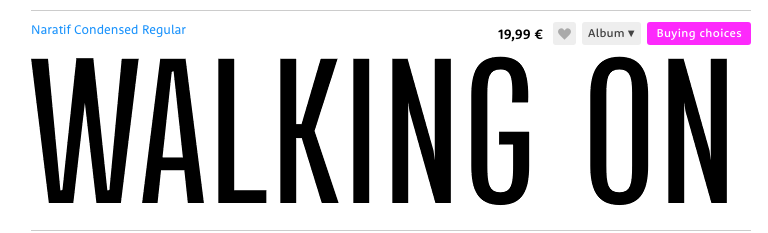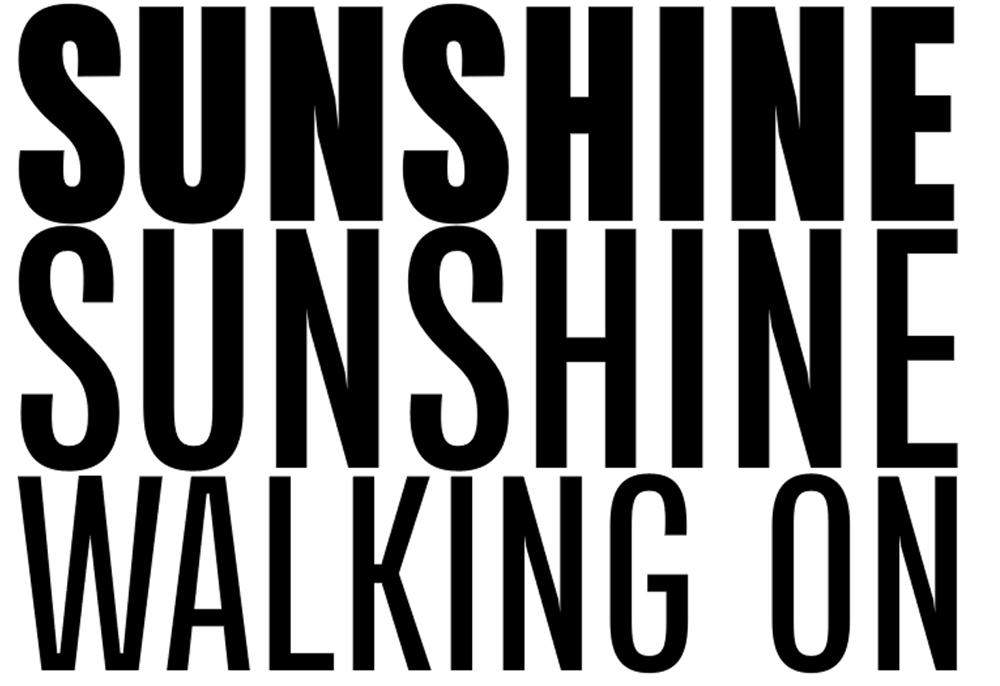
Ein Kunde verlangt nach genau dieser Schrift (hat sich die Schriftmuster auf einer Downloadseite zusammengestellt, weiß aber weder auf welcher noch den/die Schriftnamen). Wie immer, wenn's um eine (scheinbar) klassische Sans Serif geht, komm’ ich bei so wenigen Glyphen zu keiner eindeutigen Lösung?
Kann mir wer helfen? 3 Schnitte einer Familie? Verschiedene Schriften? (Müssen natürlich nicht kostenlos sein…)